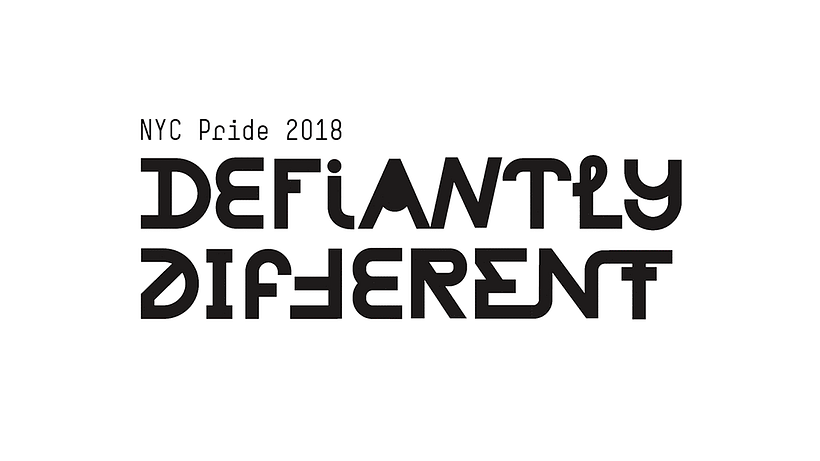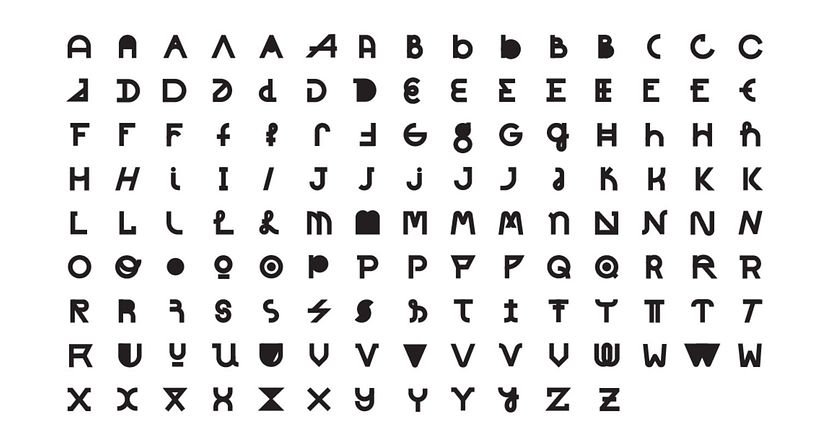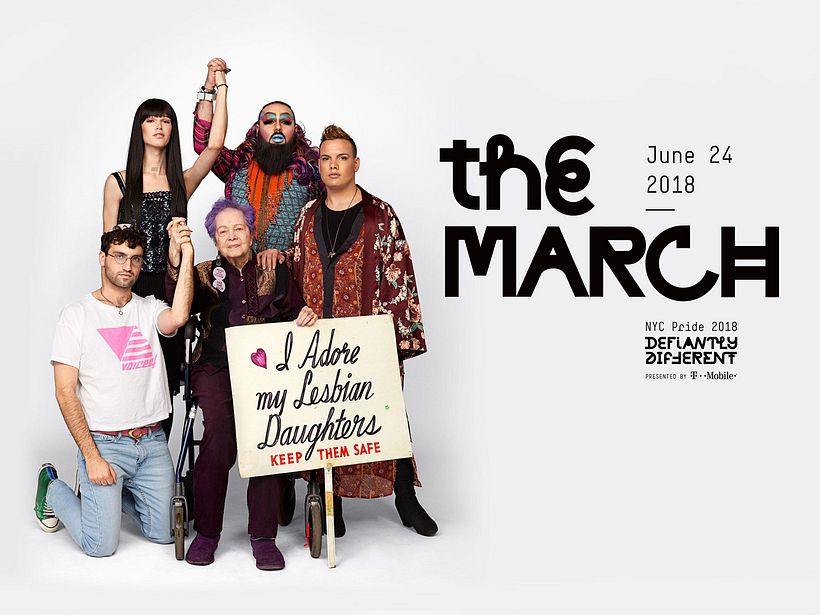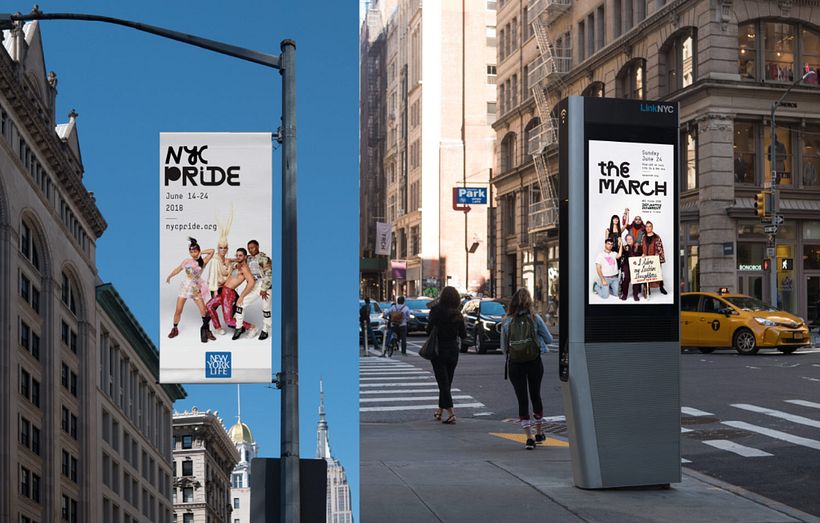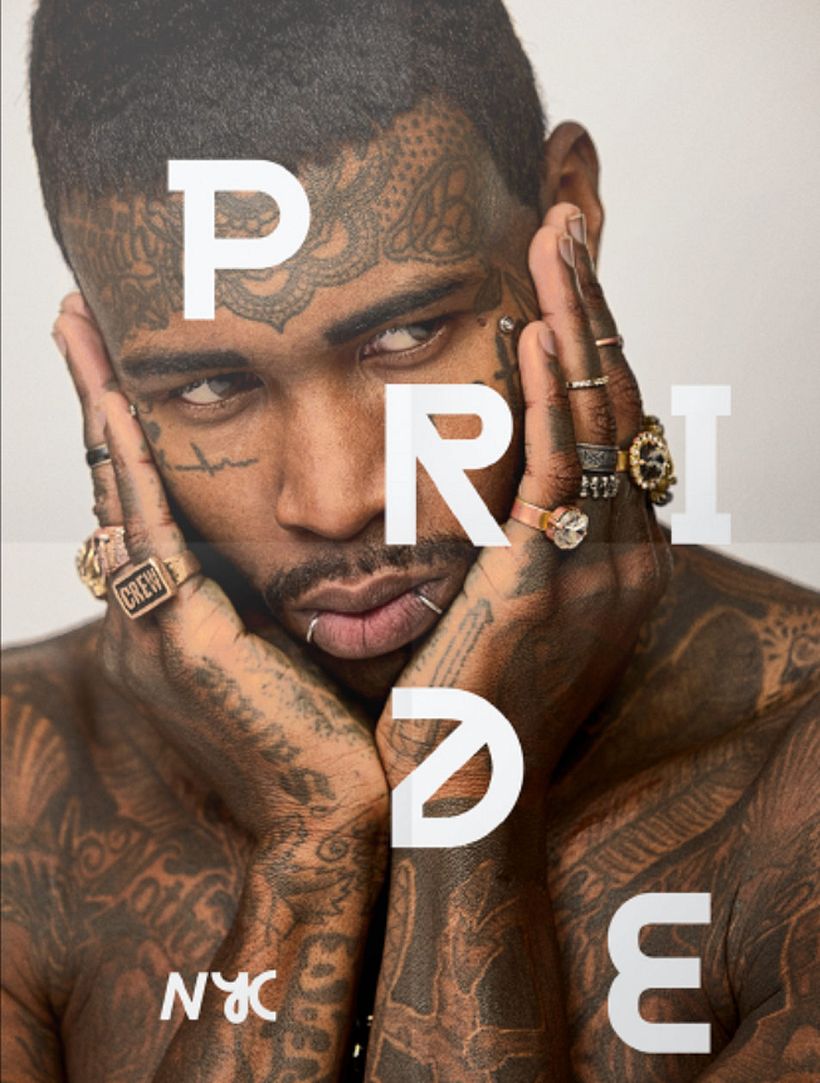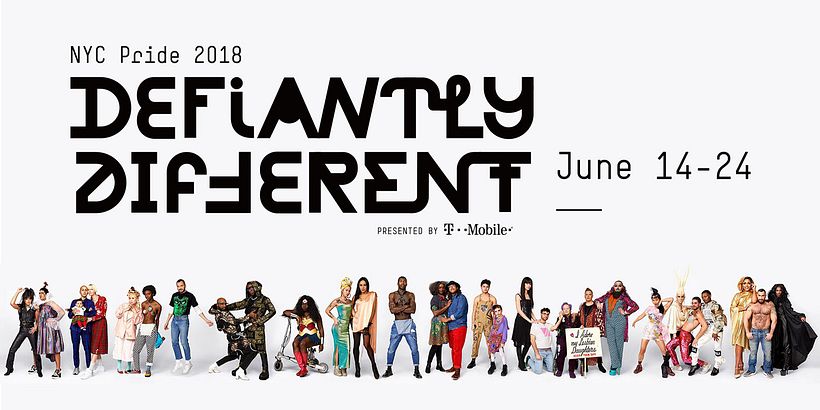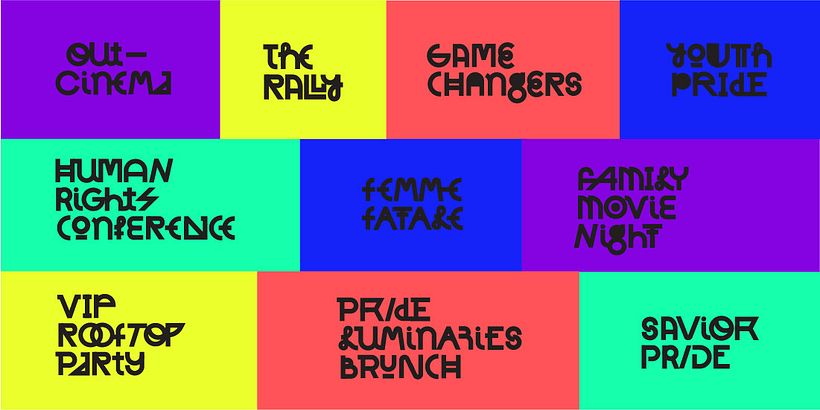
Defiantly Different, una tipografía que celebra la diversidad
La celebración del Día Internacional del Orgullo de Nueva York ha traído consigo una gran tipografía: Defiantly Different.
'Defiantly Different' (desafiantemente diferente) es el lema que la campaña del Orgullo de Nueva York ha tomado por bandera, y es también el nombre de la tipografía que la agencia Grey ha diseñado para celebrar el evento. Se trata de una tipografía en la que cada glifo ha sido creado con características únicas, pero al mismo tiempo ha sido pensado para encajar a la perfección con el resto de la familia tipográfica. Además, existe más de un glifo para cada letra, de manera que las combinaciones se vuelven infinitas y el mensaje queda más que claro: abrazar la diversidad.
Aunque el movimiento LGBTQ+ se caracteriza por la inclusividad, la incorporación de nuevas letras a sus siglas y movimientos como el de Daniel Quasar, quien proponía rediseñar la bandera del Orgullo para representar la diversidad (agregando los colores que representan a las comunidades trans y queer más marginadas), ponen de manifiesto la necesidad de dar visibilidad a realidades que van mucho más allá del amor por las personas del mismo sexo y se mueven en el plano de la propia identidad sexual y de género. Y, precisamente, la tipografía Defiantly Different ha sido diseñada con esto en mente, de manera que cada glifo es completamente diferente al anterior, resaltando características únicas y las alternativas han sido creadas para que cada una mantenga con orgullo su propia identidad.
Desde Eye on Design han preguntado a sus creadores acerca del uso para el que fue pensada y como cabía esperar, la respuesta no ha dejado lugar a dudas: Defiantly Different fue diseñada para ser vista y por eso encaja a la perfección en titulares y carteles que tienen algo que contar y quieren decirlo alto y claro. Otra cuestión interesante es la de con qué otras tipografías encaja y en este caso, según sus diseñadores se trata de una fuente con carácter que no resulta fácil combinar, aunque proponen tipografías sin serifa como Stratos o Schwiss.